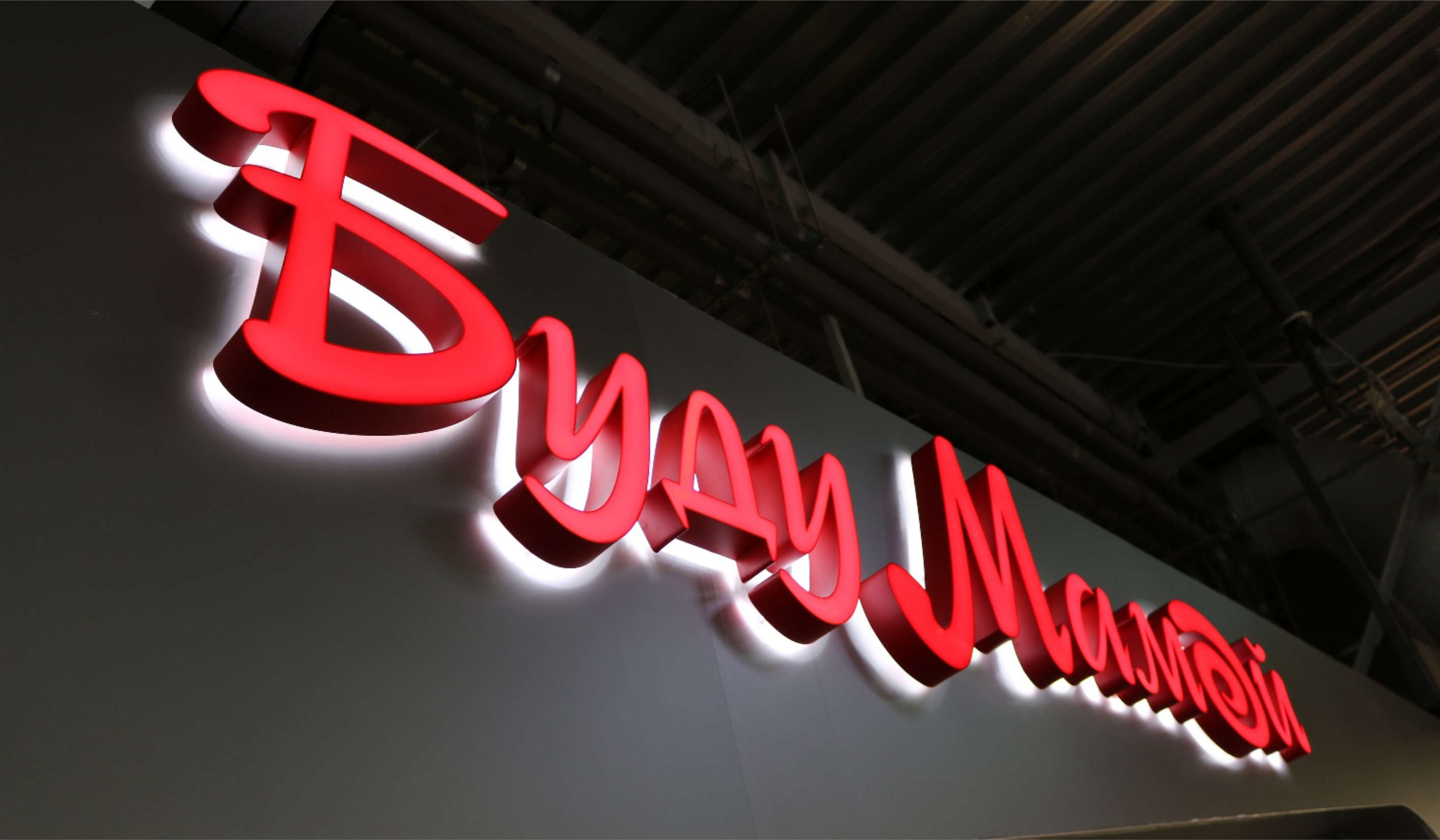
Как выбрать шрифт для наружной рекламной вывески
При выборе шрифта, подходящего для применения в наружной рекламе торгового центра, дизайнер старается одновременно учитывать несколько важных факторов. Шрифт должен иметь привлекательность, украшать рекламу, работать на ее пользу.
Как выбрать шрифт
Правила, которыми руководствуются наши эксперты при выборе подходящей вывески, подходят для кафе, ресторана, салона красоты, магазина, организации и т.д. Мы оформляем вариант вывески, но клиенты могут и сами определять, что им нужно в их конкретной ситуации.
Рекомендуемое количество шрифтов не должно превышать двух. В основе разработки шрифтов должно быть их соответствие стилевому оформлению, легкость восприятия, сочетание между собой.
Надписи на вывесках не должны содержать шрифты, сложные для чтения
Шрифты должны быть простыми для прочтения
Шрифты бывают трех типов. Расскажем об их применении к рекламным вывескам.
Шрифты с засечками или антиква
Шрифты с засечками называют Serif.
Свойство засечек направлять движение глаз вдоль строк считается особенно полезным при чтении текстов с большими буквами. Такой шрифт воспринимается в качестве более устойчивого, ведь он придает тексту официальности.
При изготовлении объемных символов для рекламной вывески многие государственные компании применяют этот тип шрифта. Такие шрифты также могут применяться на зданиях исторического значения, ведь на них они выглядят очень гармонично.
Применение шрифтов с засечками
Шрифты без засечек или рубленные шрифты
Данные шрифты в Америке называются Gothic, в Германии Grotesk, а в Англии- Sans Serif. Штрихи на линиях символов в таких шрифтах отсутствуют.Как правило толщина основных и соединительных шрифтов букв является практически одинаковой, поэтому рубленные шрифты можно характеризовать определенной легкостью и современностью.
С помощью таких шрифтов можно легко менять расстояние между буквами, поэтому их часто используют в дизайнерском деле.
Шрифт крупного размера, набранный гротеском, воспринимается целостно, в качестве единого пятна. Его используют в рекламных материалах и заголовках, в т.ч. в процессе изготовления вывесок.
Декоративные шрифты
Декоративные шрифты в основном являются имитацией ручного написания и различными вариантами курсива. С помощью таких шрифтов украшают и расставляют акценты в рекламных материалах.
Прописные или строчные
Заглавная буква должна быть вначале текста вывески, состоящего из строчных символов. При использовании прописных символов, применяется разрядка. Символы без интервала не читаются, налезают друг на друга и визуально сливаются. Хотя при сильном ограничении места под вывеску, можно говорить об исключении из этого правила.
Выравнивание надписей по горизонтали и вертикали в вывесках
Межсимвольный интервал должен быть одинаковым, при использовании на вывеске шрифта одинакового размера и применении в названии компании нескольких строчек.
Если название вашей фирмы состоит из несколько строчек, и на вывеске используется шрифт одного размера, то межбуквенный интервал должен быть одинаковым.
Расположение букв «ногами» к фасаду является самым лучшим вариантом вертикального расположения текста рекламной вывески.
Расстояние между строк
Шрифт одного размера должен использоваться в тексте вывески, который состоит из одного предложения.
Первая строчка из двух используемых шрифтов одинакового размера должна состоять из заглавных букв. Для остальных строчек применяются прописные символы. Таблица характеризуется приятностью и лаконичным видом.
Подходит ли стиль здания к шрифту
Архитектурный облик зданий может быть выражен не всеми типами шрифтом. При этом вы можете использовать любой тип шрифта, какой только сами пожелаете.
Шрифт одного размера отлично подходит для случаев, когда текст состоит из одного предложения. Два шрифта используются в текстах, которые состоят из двух и более строк.
Выводы
Все описанные в статье правила не являются обязательными для использования и имеют исключительно рекомендательный характер. При использовании правил необходимо учитывать особенности конкретного товара и выбранного вида рекламного носителя.
Дизайнеры нашей компании помогут каждому, кто сомневается в правильности собственного выбора. Особый пункт в нашей работе занимают дизайнерские шрифты, которые выполняются с целью придания компании и ее продукции дополнительной узнаваемости.
Какой шрифт выбрать для рекламной вывески?
Как выбрать необходимый шрифт для наружной рекламы
Когда наш дизайнер работает над макетом будущей вывески, он выбирает из множества шрифтов те, которые подойдут фирменному стилю магазина. Так как шрифт должен привлекать внимание потенциальных покупателей, и качественно рекламировать продукт.
10 шрифтов, идеально подходящих для вывесок
Независимо от того, решили ли вы нанять графического дизайнера или собираетесь заниматься этим собственными силами, предварительное определение определенных характеристик вашей вывески может помочь вашей вывеске остаться на бренде и обеспечить ее эффективность.В этой статье мы рассмотрим, какие шрифты следует учитывать при разработке нового знака.
Гельветика